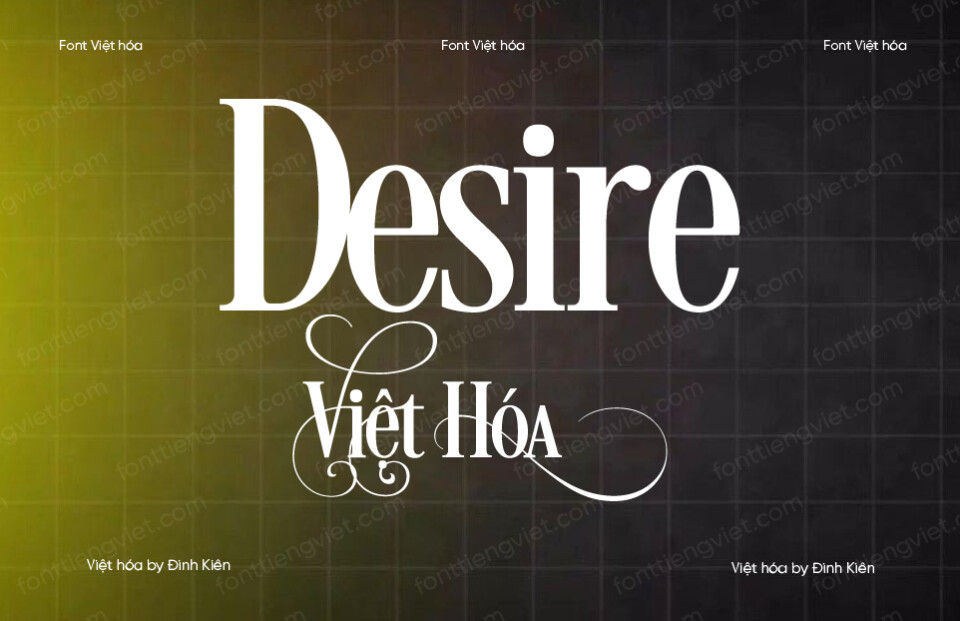
Trong thế giới thiết kế đồ họa đầy màu sắc và không ngừng biến đổi, việc lựa chọn một Font Chữ phù hợp có vai trò cực kỳ quan trọng trong việc truyền tải thông điệp và tạo ấn tượng thị giác mạnh mẽ. Trong số vô vàn lựa chọn, Font Việt hóa UTM Desire đã nổi lên như một ngôi sao sáng, thu hút sự chú ý của cộng đồng thiết kế nhờ vẻ đẹp độc đáo và tính ứng dụng cao. Không chỉ mang đến sự thanh lịch và hiện đại, UTM Desire còn được yêu thích bởi khả năng tương thích hoàn hảo với tiếng Việt, mở ra không gian sáng tạo bất tận cho các dự án từ cá nhân đến chuyên nghiệp. Bài viết này sẽ đi sâu khám phá những đặc điểm nổi bật, lý do tại sao UTM Desire lại được ưa chuộng, và cách ứng dụng font này một cách hiệu quả để tạo ra những tác phẩm thiết kế đẳng cấp.
Tại Sao Font Việt hóa UTM Desire Lại Được Ưa Chuộng?
Sự nổi tiếng của Font Việt hóa UTM Desire không phải là ngẫu nhiên mà đến từ sự kết hợp hài hòa giữa tính thẩm mỹ và công năng sử dụng. Một trong những yếu tố hàng đầu khiến font này được lòng giới thiết kế chính là vẻ đẹp thanh thoát, tinh tế. UTM Desire sở hữu những đường nét mềm mại nhưng vẫn giữ được sự mạnh mẽ cần thiết, tạo nên một phong cách độc đáo, khó lẫn. Kiểu chữ này có khả năng biến hóa linh hoạt, phù hợp với nhiều phong cách thiết kế khác nhau, từ cổ điển đến hiện đại, từ tối giản đến phức tạp. Điều này giúp các nhà thiết kế dễ dàng tạo ra sự đồng nhất trong nhận diện thương hiệu hoặc sự đa dạng trong các ấn phẩm truyền thông mà không làm mất đi tính chuyên nghiệp.
Thêm vào đó, khả năng Việt hóa hoàn chỉnh là một điểm cộng lớn. Đối với người Việt Nam, việc sử dụng các font chữ nước ngoài thường gặp khó khăn với các ký tự dấu, gây lỗi hiển thị hoặc mất đi tính thẩm mỹ tổng thể. Font Việt hóa UTM Desire đã khắc phục hoàn toàn vấn đề này, đảm bảo mọi ký tự tiếng Việt đều được hiển thị một cách trọn vẹn, rõ ràng và đẹp mắt. Điều này không chỉ giúp tiết kiệm thời gian chỉnh sửa mà còn nâng cao chất lượng bản dịch và sự chuyên nghiệp của sản phẩm cuối cùng. Từ các tài liệu học tập cho học sinh, sinh viên đến các ấn phẩm quảng cáo cao cấp, UTM Desire đều chứng tỏ được giá trị của mình.
Đặc Điểm Nổi Bật Của UTM Desire
UTM Desire được thiết kế với sự tỉ mỉ trong từng chi tiết, tạo nên một bộ font có chiều sâu và cá tính riêng. Font này thường có các nét thanh và đậm được điều chỉnh khéo léo, tạo nên sự cân bằng thị giác ấn tượng. Độ giãn cách giữa các ký tự (kerning) và khoảng cách dòng (leading) cũng được tối ưu hóa, đảm bảo khả năng đọc tốt ngay cả ở kích thước nhỏ hoặc trên các nền phức tạp. Sự đa dạng về trọng lượng (light, regular, bold, v.v.) và kiểu dáng (italic) cũng là một lợi thế, cho phép các nhà thiết kế linh hoạt lựa chọn để tạo điểm nhấn hoặc phân cấp thông tin một cách hiệu quả. Đây là một yếu tố quan trọng giúp cho việc thiết kế những ấn phẩm dành cho lứa tuổi học sinh, sinh viên trở nên cuốn hút và dễ tiếp cận hơn.
Bên cạnh đó, Font Việt hóa UTM Desire còn nổi bật với khả năng kết hợp hài hòa với các font khác. Dù được sử dụng độc lập hay kết hợp với một kiểu chữ sans-serif đơn giản, UTM Desire vẫn giữ được sự nổi bật và tạo ra hiệu ứng thị giác mạnh mẽ. Sự linh hoạt này giúp font trở thành lựa chọn lý tưởng cho việc tạo ra logo, tiêu đề ấn phẩm, poster, banner, hay thậm chí là nội dung chính trong các tài liệu đòi hỏi tính thẩm mỹ cao. Với một kiểu chữ đẹp như UTM Desire, thông điệp truyền tải sẽ trở nên sống động và thu hút hơn rất nhiều.
Ứng Dụng Đa Dạng Của Font Này Trong Thiết Kế
Font Việt hóa UTM Desire có thể được ứng dụng trong rất nhiều lĩnh vực khác nhau, chứng minh tính đa năng của nó. Trong thiết kế thương hiệu, font này thường được sử dụng để tạo logo, tagline, và bộ nhận diện thương hiệu, mang đến vẻ đẹp sang trọng và hiện đại cho doanh nghiệp. Đối với các ấn phẩm in ấn như tạp chí, sách báo, poster, brochure, UTM Desire giúp thu hút người đọc ngay từ cái nhìn đầu tiên và tạo cảm giác chuyên nghiệp. Trong thiết kế website và ứng dụng di động, font này đảm bảo tính thẩm mỹ và khả năng đọc tốt trên mọi thiết bị, nâng cao trải nghiệm người dùng.
Ngoài ra, UTM Desire cũng rất được ưa chuộng trong lĩnh vực giáo dục và thi cử. Từ các bài giảng, tài liệu học tập, đến đề thi tốt nghiệp trung học phổ thông hay các kỳ thi quan trọng khác, việc sử dụng một font chữ rõ ràng, dễ đọc như UTM Desire giúp học sinh, sinh viên tập trung hơn vào nội dung và giảm mệt mỏi thị giác. Nó cũng góp phần tạo nên một hình ảnh chuyên nghiệp và đáng tin cậy cho các tài liệu giáo dục. Sự rõ ràng và tính thẩm mỹ của font giúp các thông tin quan trọng được truyền tải một cách hiệu quả.
Hướng Dẫn Sử Dụng Font UTM Desire Hiệu Quả
Để tận dụng tối đa vẻ đẹp của Font Việt hóa UTM Desire, các nhà thiết kế cần lưu ý một số nguyên tắc. Đầu tiên, hãy sử dụng font này một cách có chủ đích. UTM Desire rất phù hợp cho tiêu đề, logo, hoặc các phần văn bản cần tạo điểm nhấn. Với các đoạn văn bản dài, bạn có thể cân nhắc kết hợp với một font sans-serif hoặc serif cơ bản, dễ đọc hơn để đảm bảo sự thoải mái cho người đọc. Việc lựa chọn màu sắc và kích thước font cũng rất quan trọng, đảm bảo sự hài hòa với tổng thể thiết kế và dễ dàng đọc được trên mọi nền.
Thứ hai, luôn kiểm tra kỹ lưỡng các ký tự tiếng Việt sau khi áp dụng font. Mặc dù đã được Việt hóa hoàn chỉnh, việc kiểm tra lại vẫn là một bước quan trọng để đảm bảo không có bất kỳ lỗi hiển thị nào phát sinh, đặc biệt là với các dấu câu phức tạp hoặc khi xuất bản lên các nền tảng khác nhau. Cuối cùng, đừng ngại thử nghiệm. Font Việt hóa UTM Desire có nhiều biến thể và khả năng kết hợp phong phú. Hãy thử nghiệm với các trọng lượng khác nhau, kết hợp với hình ảnh, màu sắc để tìm ra phong cách phù hợp nhất cho dự án của bạn, từ những dự án đơn giản của học sinh đến các ấn phẩm chuyên nghiệp đòi hỏi sự tinh tế cao.
Nhìn chung, Font Việt hóa UTM Desire không chỉ là một kiểu chữ đẹp mắt mà còn là một công cụ mạnh mẽ trong tay của bất kỳ nhà thiết kế nào. Với sự kết hợp hoàn hảo giữa tính thẩm mỹ, khả năng dễ đọc và sự hỗ trợ tiếng Việt đầy đủ, font này đã và đang khẳng định vị thế của mình trong ngành thiết kế đồ họa. Cho dù bạn là một học sinh đang thực hiện dự án trường học, một sinh viên thiết kế đang tìm kiếm nguồn cảm hứng, hay một chuyên gia muốn nâng tầm thương hiệu, UTM Desire chắc chắn sẽ là một lựa chọn đáng giá để cân nhắc. Hãy khám phá và để Font Chữ này chắp cánh cho những ý tưởng sáng tạo của bạn.